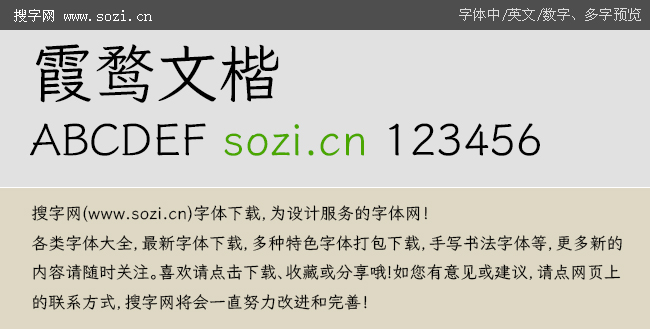
霞鶩文楷
搜字網(wǎng)給大家提供一款霞鶩文楷中文字體下載,霞鶩文楷是@落霞孤鶩基于日本著名字體廠商Fontworks的Klee One開源字體進(jìn)行補(bǔ)字而成的一套更適合國內(nèi)用戶使用的免費(fèi)可商用字體。霞鶩文楷兼有仿宋和楷體的特點(diǎn),可讀性高,無論是在手機(jī)還是電腦上使用都非常漂亮。適用于海報(bào)設(shè)計(jì)、包裝設(shè)計(jì)、廣告設(shè)計(jì)等場景。